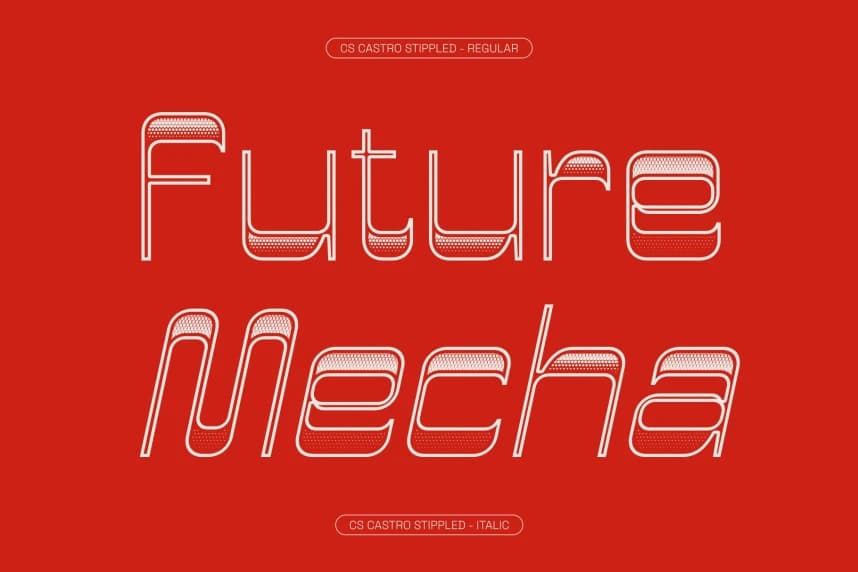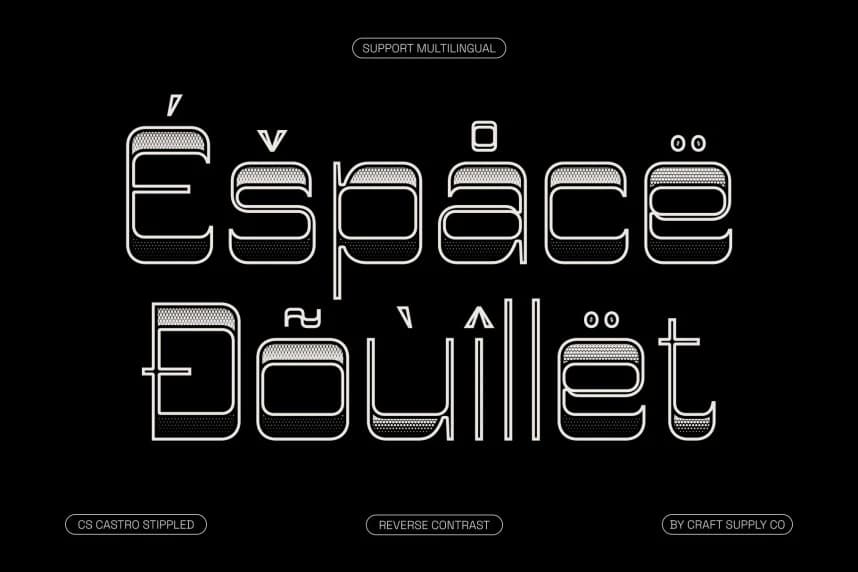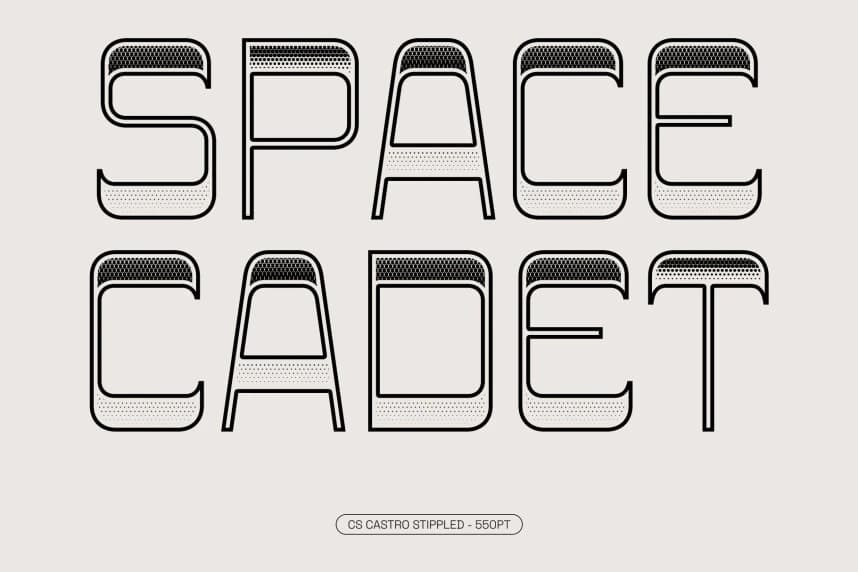
CS Castro Stippled Font
CS Castro Stippled Font – Reverse Contrast Font with Textured Retro Character Sans-Serif with Reverse Contrast Style. Bu, modern tasarım ilkelerini ters kontrastın benzersiz görsel ritmiyle birleştiren ayırt edici bir sans-serif yazı tipidir.
CS Castro Stippled Font – Ters Kontrast Fontu, Dokulu Retro Karakter Sans-Serifi ile Ters Kontrast Stili. Bu, modern tasarım ilkelerini ters kontrastın özgün görsel ritmiyle birleştiren ayırt edici bir sans-serif yazı tipidir.
CS Castro Stippled
CS Castro Stippled Regular